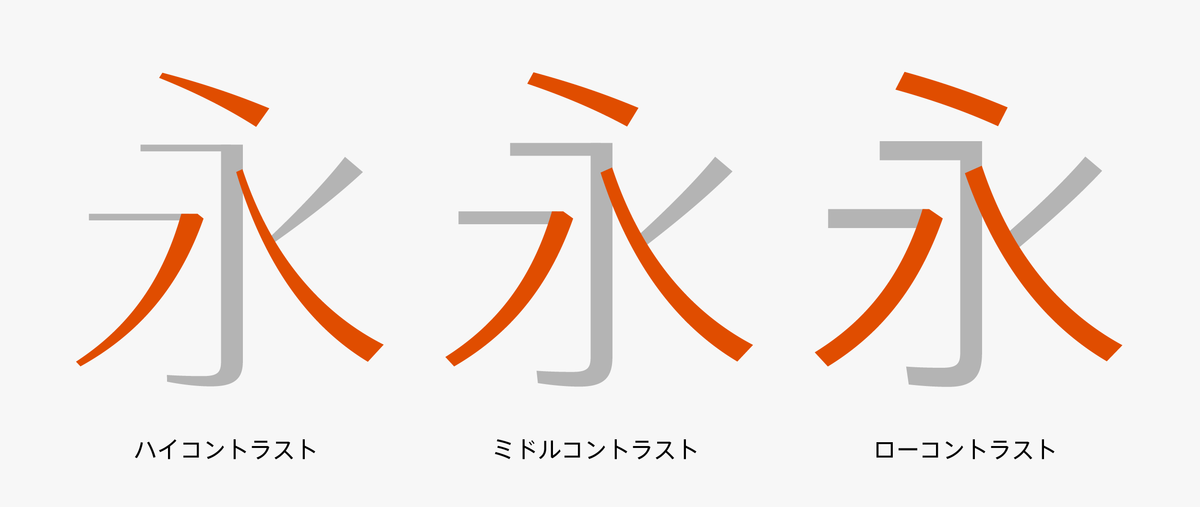
タイププロジェクトがTPスカイ クラシックシリーズの拡張として、筆の抑揚を取り入れた古典的な表情の「ハイコントラスト」と「ミドルコントラスト」を発表
タイププロジェクは、スクリーン表示に最適な「TPスカイ」ファミリーに、シャープな印象の「TPスカイ クラシック ハイコントラスト」と穏やかながらも表情ゆたかな「TPスカイ クラシック ミドルコントラスト」を追加したことを2021年10月1日に発表した。
「TPスカイ クラシック」の漢字・仮名・欧文を貫く均整の取れたプロポーションは、画面を引き締めると同時に落ち着いた雰囲気を醸し出している。
引き締まったフトコロ(字画内の内部空間)と伸びやかなストロークの対比が持ち味で、フトコロ軸とコントラスト軸(ハイ、ミドル、ロー)の連携により、クラシックな印象を高めている。
「はらい」や「てん」などに筆の抑揚を取り入れたハイルコントラストとミドルコントラストでは、ローコントラストよりも古典的な表情が強まり、端正な古典楷書に範をとったTPスカイ クラシックの方向性をより明確に表現した。
「TPスカイ クラシック ハイコントラスト」と「TPスカイ クラシック ミドルコントラスト」の追加で、TPスカイファミリーは、TPスカイ45フォント(5ウエイト×3コントラスト×3つの字幅)、TPスカイ クラシック(5ウエイト×3コントラスト)、TPスカイ モダン ブラックで、合計61フォントのラインナップとなった。
タイププロジェクトの代表取締役 鈴木功氏は、「ストロークの先端部に飾りがなく、抑揚の強弱がないサンセリフ体は、デジタル環境に適したシンプルさと安定した読み心地を持ち味とする一方、単調な表情になりがちです。TPスカイ クラシックでは、この主要な書体カテゴリーであるサンセリフ体に、フトコロの概念を導入することで現代的な用途の書体に古典的な表情を添えました。3つのコントラストが揃ったTPスカイ クラシックシリーズを楽しんでお使いいただけれと思います。」とコメントしている。